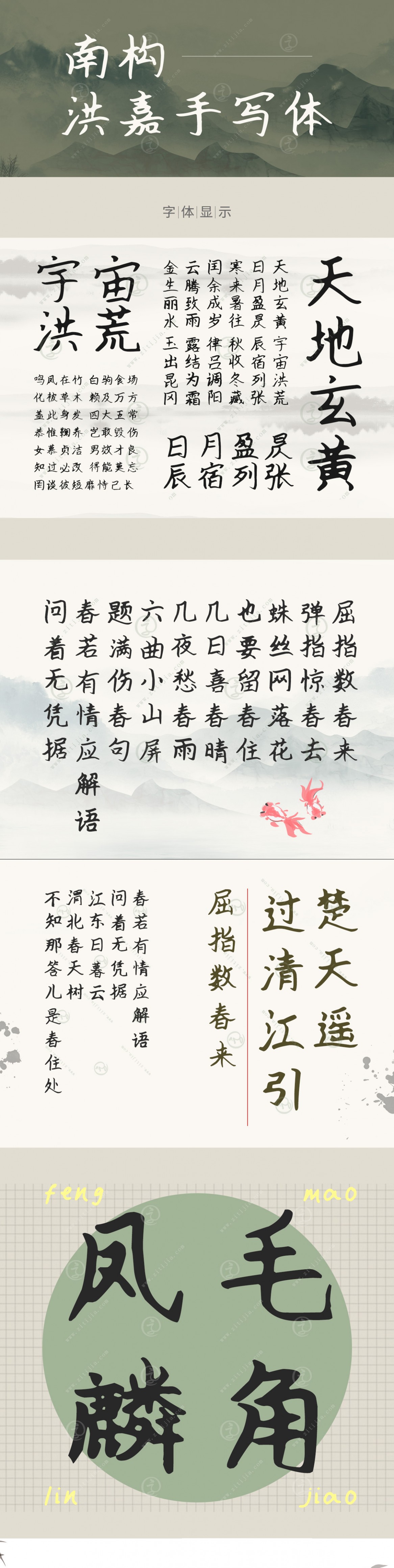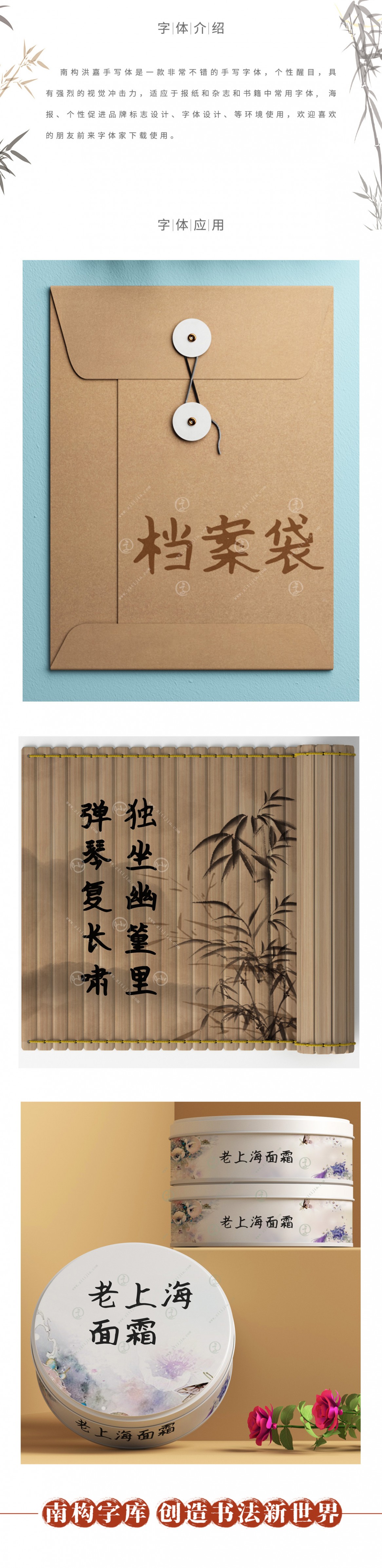
南構(gòu)洪嘉手寫(xiě)體
南構(gòu)洪嘉手寫(xiě)體是一款非常不錯(cuò)的手寫(xiě)字體,個(gè)性醒目,具有強(qiáng)烈的視覺(jué)沖擊力,適應(yīng)于報(bào)紙和雜志和書(shū)籍中常用字體, 海報(bào)、個(gè)性促進(jìn)品牌標(biāo)志設(shè)計(jì)、字體設(shè)計(jì)、等環(huán)境使用,歡迎喜歡的朋友前來(lái)下載使用。